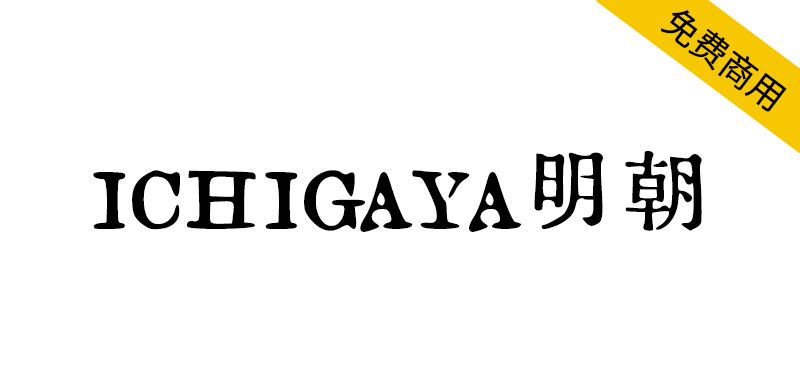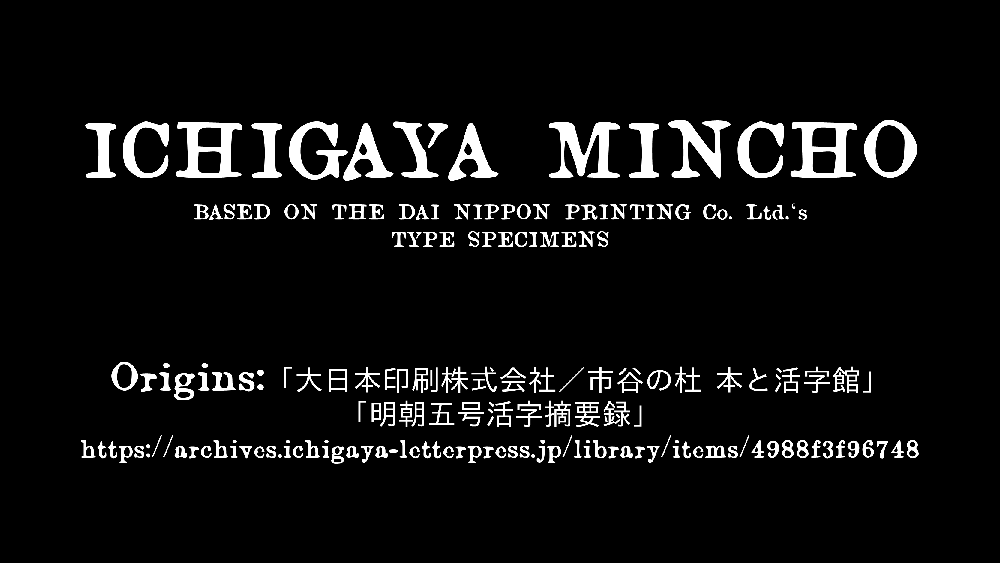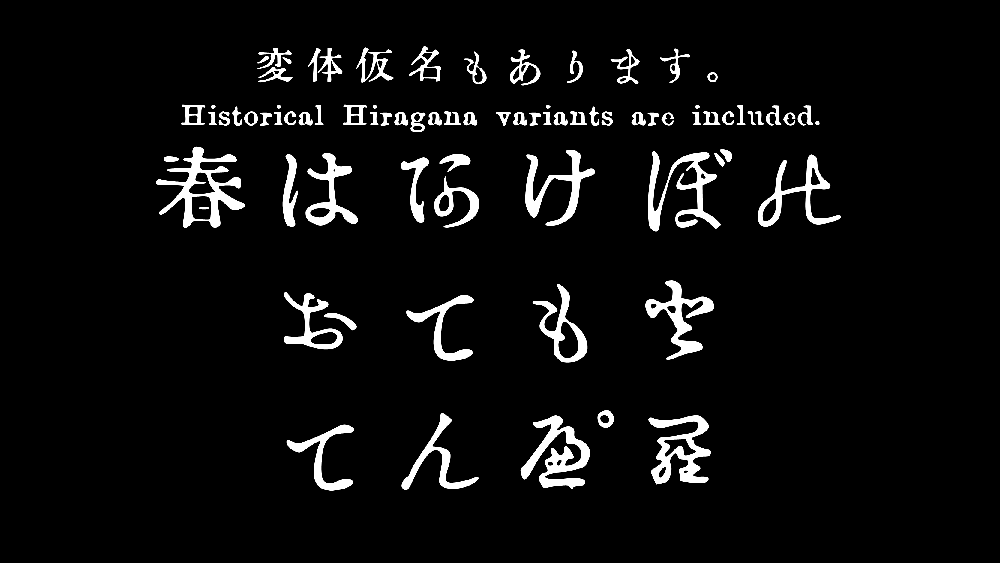
【ICHIGAYA明朝】基于日本企业秀英舍活版制造所的活字样本制作
你见过1913年活字印刷的“明朝体”如何重生为现代设计利器吗?ICHIGAYA明朝字体,源自日本秀英舍活版制造所珍贵样本,复刻自《明朝五号活字摘要録》,融合百年工艺与数字技术,免费商用却极具历史质感。它为何能成为设计师手中的复古新宠?适用范围与限制全解析,一文看懂这款跨越时代的字体背后的故事。
【ICHIGAYA明朝】基于日本企业秀英舍活版制造所的活字样本制作
ICHIGAYA明朝(ICHIGAYAMincho)是一种复古字体,基于大日本印刷株式会社前身企业秀英舍活版制造所的活字样本,通过InkScape软件的自动描摹功能制作而成,主要字形来源市谷杜本和活字馆所有的《明朝五号活字摘要録》(1913年),部分文字参考了《活字注文用当用漢字表》(1946年)、《活版見本帖 Type Specimens(仮)》(1914年)。